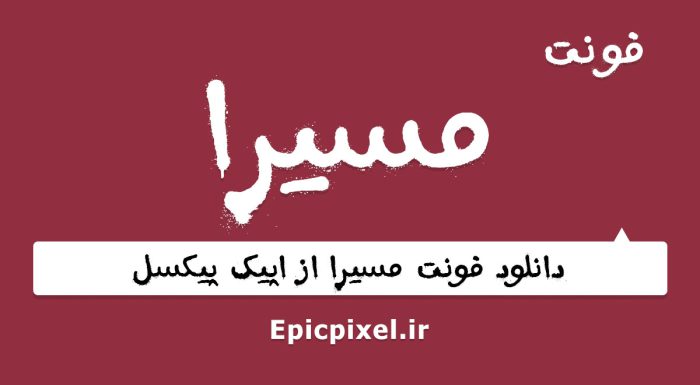
فونت مسیرا فارسی Massira
فونت مسیرا فارسی عربی، به طور خاص نسخه Massira 29LT، یک قلم با طراحی متمایز و اصلاح شده برای زبان های فارسی و عربی است بصورت رایگان. ویژگی برجسته و اصلی این فونت، ظاهر آن با حالت دیوار نویسی اسپری شده است که به حروف جلوه ای هنری، پویا و یادآور سبک گرافیتی می بخشد. Massira 29LT با این استایل بصری قوی، گزینه ای ایده آل برای خلق عناوین، تیترها و طرح های گرافیکی با تم های شهری، هنری یا غیررسمی محسوب می شود و تأثیر بصری چشمگیری ایجاد می کند.
شناخت فونت هایی که با سبک های بصری خاص و غیرمتعارف ارائه می شوند، می تواند به طراحان در خلق آثاری متمایز و خلاقانه کمک شایانی کند. فونت مسیرا فارسی عربی که به طور خاص با عنوان Massira 29LT شناخته می شود، یکی از این قلم ها است که به طور ویژه برای استفاده در زبان های فارسی و عربی اصلاح و آماده سازی شده تا سازگاری کاملی با این خطوط داشته باشد.
ویژگی اصلی و بسیار متمایز کننده این فونت که هویت بصری آن را شکل می دهد، ظاهر آن با حالت دیوار نویسی اسپری شده است. این سبک منحصربه فرد، جلوه ای خام، بافت دار، پویا و هنری به حروف می بخشد که به وضوح یادآور هنر گرافیتی و نوشتارهای سریع و پرانرژی دیواری است. این قلم برای پروژه هایی مناسب است که به دنبال انتقال حس شور، آزادی بیان، خلاقیت و فضای فرهنگی شهری هستند و می خواهند متونشان ظاهری غیررسمی، جسورانه و هنری داشته باشد.
عنوان ’29LT’ بخشی از نام این فونت است که آن را در خانواده Massira مشخص می کند و به این نسخه خاص با سبک دیوارنویسی اسپری شده اشاره دارد. تمرکز اصلی این نسخه بر روی ارائه همین سبک خاص بصری برای متون فارسی و عربی است.
دانلودبا توجه به ماهیت تزئینی و سبک بصری قوی، فونت مسیرا 29LT عمدتاً برای استفاده در مقاصد نمایشی (Display) طراحی شده است. این سبک نوشتاری برای عناوین اصلی، تیترهای بزرگ، طراحی پوسترها، بنرها، جلد آلبوم های موسیقی، طرح های مرتبط با مد خیابانی یا فرهنگ جوانان و کلیه پروژه هایی با تم گرافیتی یا هنری بسیار مناسب است. هرچند این فونت برای متن های طولانی و بدنه متن توصیه نمی شود، اما در اندازه های بزرگ، تأثیر بصری فوق العاده ای ایجاد می کند و فوراً توجه مخاطب را جلب می نماید. ظاهر متمایز این فونت آن را به ابزاری قدرتمند برای پروژه هایی با نیاز به جلوه ای غیرمتعارف و هنری تبدیل کرده است.
کاربردهای فونت مسیرا 29LT در برنامه های گرافیکی
با توجه به سبک خاص دیوار نویسی اسپری شده و پشتیبانی از زبان های فارسی و عربی، فونت مسیرا 29LT در برنامه های طراحی گرافیکی کاربرد فراوانی در زمینه خلق آثار بصری خاص و هنری دارد. در محیط ویندوز و مک، طراحان می توانند از این فونت در نرم افزارهایی مانند Adobe Photoshop، Illustrator، InDesign برای خلق پوسترها، بنرها، طرح های گرافیکی برای شبکه های اجتماعی، جلد آلبوم ها، و اقلام تبلیغاتی با تم شهری و هنری استفاده کنند. این فونت همچنین در اپلیکیشن های موبایل که از فونت های سفارشی پشتیبانی می کنند (نظیر Inshot یا متن نگار در اندروید و برخی اپلیکیشن های iOS)، برای طراحی پست ها، استوری ها و عکس نوشته ها با جلوه ای گرافیتی و هنری در زبان های فارسی و عربی بسیار مناسب است.